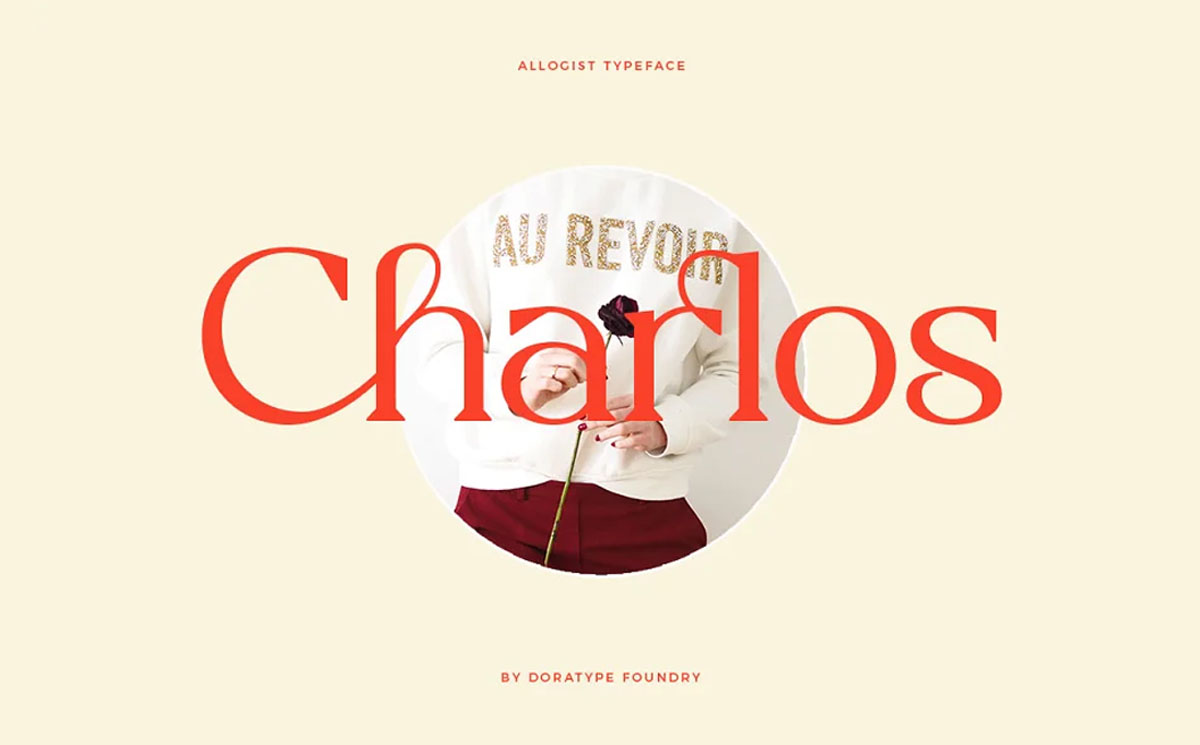
Font SVN Allogist, Phông Chữ Thanh Lịch, Hiện Đại Và Sang Trọng
Font SVN Allogist: Phông Chữ Thanh Lịch, Hiện Đại Và Sang Trọng (Việt Hóa Miễn Phí)
Trong thế giới thiết kế đồ họa, việc lựa chọn một phông chữ phù hợp quyết định rất lớn đến sự thành công của toàn bộ ấn phẩm. Nếu bạn đang tìm kiếm một bộ font mang đậm nét quyến rũ, cao cấp nhưng không kém phần đương đại, SVN Allogist chính là mảnh ghép hoàn hảo. Bài viết này sẽ giúp bạn khám phá chi tiết về nét đẹp của Font SVN Allogist bản Việt hóa, cũng như cách ứng dụng phông chữ này vào các dự án sáng tạo.
Tại Sao SVN Allogist Lại Thu Hút Các Nhà Thiết Kế?
SVN Allogist thuộc dòng font Serif (có chân) mang phong cách tân cổ điển. Sự kết hợp tinh tế giữa các đường nét dày mỏng tạo ra độ tương phản cao, mang lại cảm giác thời thượng và đẳng cấp cho bất kỳ thiết kế nào.
1. Đường Nét Thanh Lịch, Đậm Chất Hiện Đại
Khác với những phông chữ Serif truyền thống thường mang cảm giác cổ kính, Allogist được tinh chỉnh với các đường cong mượt mà và sắc nét. Chữ cái có cấu trúc cân đối, tạo ra một tổng thể hài hòa, giúp người đọc dễ dàng bị thu hút ngay từ ánh nhìn đầu tiên.
2. Bản Việt Hóa Chuẩn Xác 100%
Ứng Dụng Tuyệt Vời Của Font SVN Allogist
Với vẻ đẹp sang trọng và độ tương phản ấn tượng, phông chữ này đặc biệt tỏa sáng khi được sử dụng trong các lĩnh vực yêu cầu tính thẩm mỹ cao:
• Nhận Diện Thương Hiệu (Branding): Cực kỳ phù hợp để thiết kế logo, bộ nhận diện cho các thương hiệu thời trang, mỹ phẩm, trang sức, nhà hàng cao cấp hoặc spa.
• Thiết Kế Tạp Chí & Editorial: Sử dụng SVN Allogist làm tiêu đề chính (Headline) trên các bìa tạp chí, lookbook sẽ tạo ra điểm nhấn thị giác cực mạnh.
• Thiệp Cưới & Sự Kiện Mời: Mang lại vẻ ngoài trang nhã, lãng mạn cho các mẫu thiệp cưới hiện đại.
• Thiết Kế Web & Banner Quảng Cáo: Khi kết hợp cùng một phông chữ Sans-serif đơn giản cho phần nội dung (body text), SVN Allogist ở vị trí tiêu đề sẽ giúp giao diện website trở nên chuyên nghiệp và sang trọng hơn.